宋体是一种比较常用的中文字体,无论是在学校的作文,还是在办公文档中,亦或者在一些宣传物料中,宋体都以其清晰的可读性和优雅的设计赢得了众多用户的青睐。本文就给大家汇总一下宋体字体大全,包含了 7 个免费商用的宋体和 7 种付费授权的宋体,让你在学习和工作中,快速找到适合的宋体。
一、什么是宋体
宋体起源于宋朝,因此得名。它是一种有衬线的字体,具有鲜明的特征:笔画粗细适中,主要笔画与衬线之间有着明显的对比,整体结构看起来更加稳定和优雅。在我的视觉体验中,宋体在阅读时非常舒适,尤其是在印刷品和学术论文中,让我可以轻松捕捉到每一个字。
宋体的字形结构非常规整,给人一种严谨的感觉,因此在学术界、出版界以及官方文件中被广泛使用。宋体不仅适合印刷在纸张上,我们在互联网中的网页设计、电子书、APP等场景,也会看到宋体的使用出现。
1、思源宋体
思源宋体是一款开源的中文字体,由Adobe和Google联合开发。它的字形设计传统而现代,笔画清晰,适合各种文档和媒体使用。其开源特性使得我们可以自由使用和修改,满足不同设计需求。
2、字体圈欣意吉祥宋
字体圈欣意吉祥宋是一款具有吉祥寓意的宋体字型,设计上融入了传统美学元素。其特点是字形优雅,适合用于喜庆场合的邀请函、贺卡和宣传材料,这款宋体比较适合节日场景,能够传达出温馨和祝福的气息。
3、猫啃网风雅宋
猫啃网风雅宋是一款注重细节的现代宋体字体,具有优雅的线条和良好的可读性。适合用于文学作品、诗词和高雅的设计项目,能够为文本增添一种艺术氛围。
4、猴尊宋体
猴尊宋体是一款具有个性化特色的宋体字体,设计灵感来源于传统文化。其字形新颖且富有表现力,适合于广告、品牌设计及创意项目,这款字体比较能够突出品牌个性。
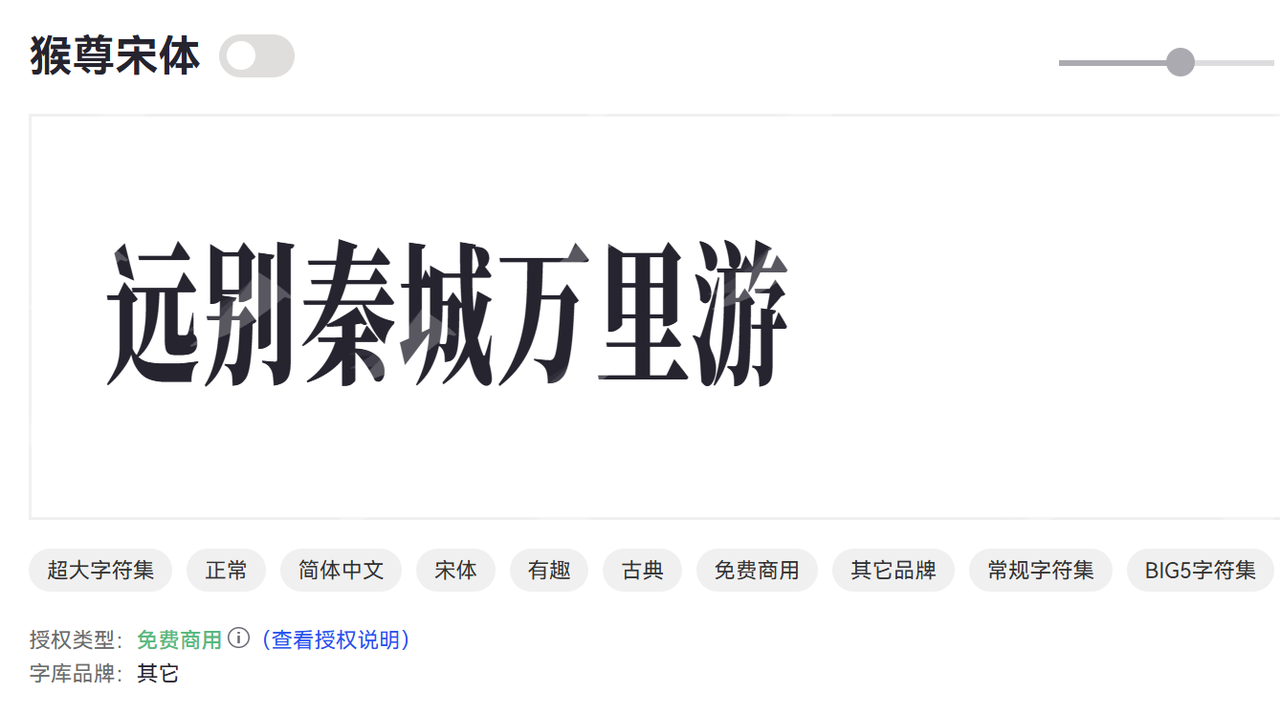
5、寒蝉活宋体
寒蝉活宋体是一款充满现代感的字体,具有动态的笔画表现。其流畅的线条使得文字在视觉上更加生动,适用于互联网文章、博客以及设计作品,能够吸引读者的注意。
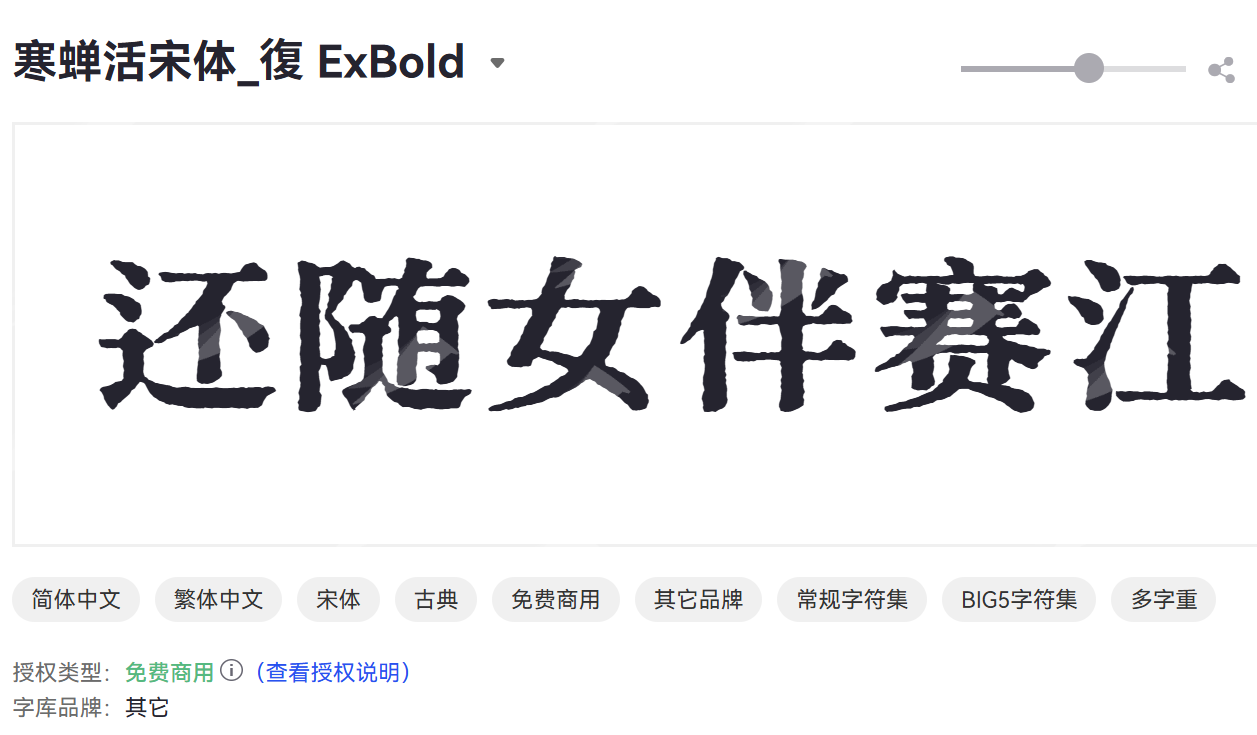
6、江城律动宋
江城律动宋是一款兼具古典与现代元素的宋体,字形稳重而灵动。该字体适用于各类正文字体,尤其是在书籍印刷和正式文件中使用,提升整体的文化氛围。
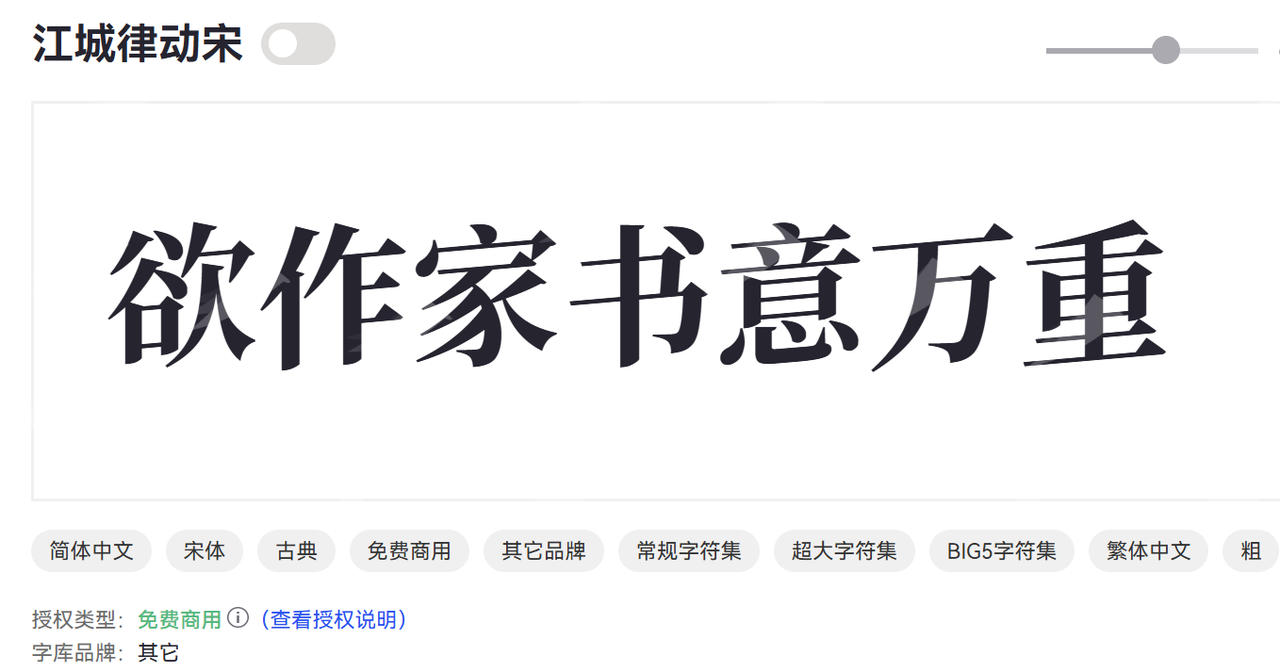
7、飞花宋体
飞花宋体是一款轻盈而富有艺术感的宋体字体,具有独特的设计风格。适合用于文艺类的设计项目、插画及装饰性文本,能够彰显出创意和美感。
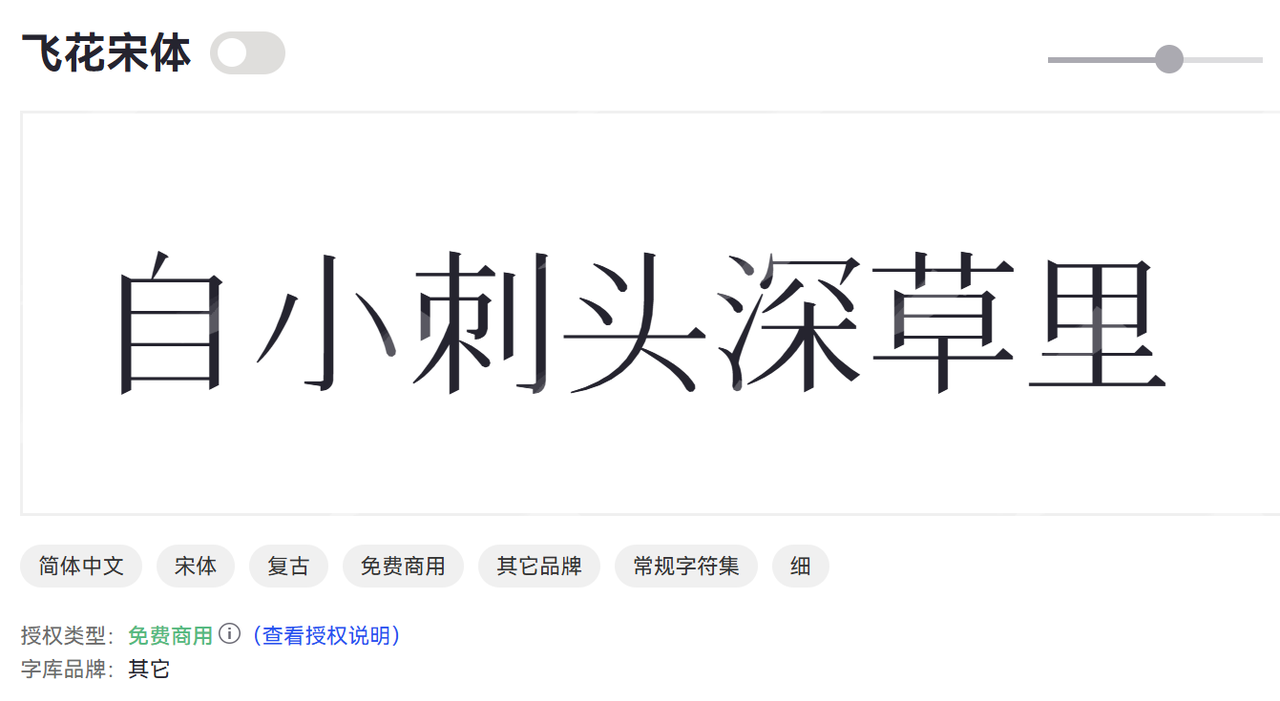
1、点字简宋
点字简宋是一款简洁明了的宋体字,强调实用性与可读性。适合用于各类普通文档和电子屏幕显示,能够保证信息的传达效率。
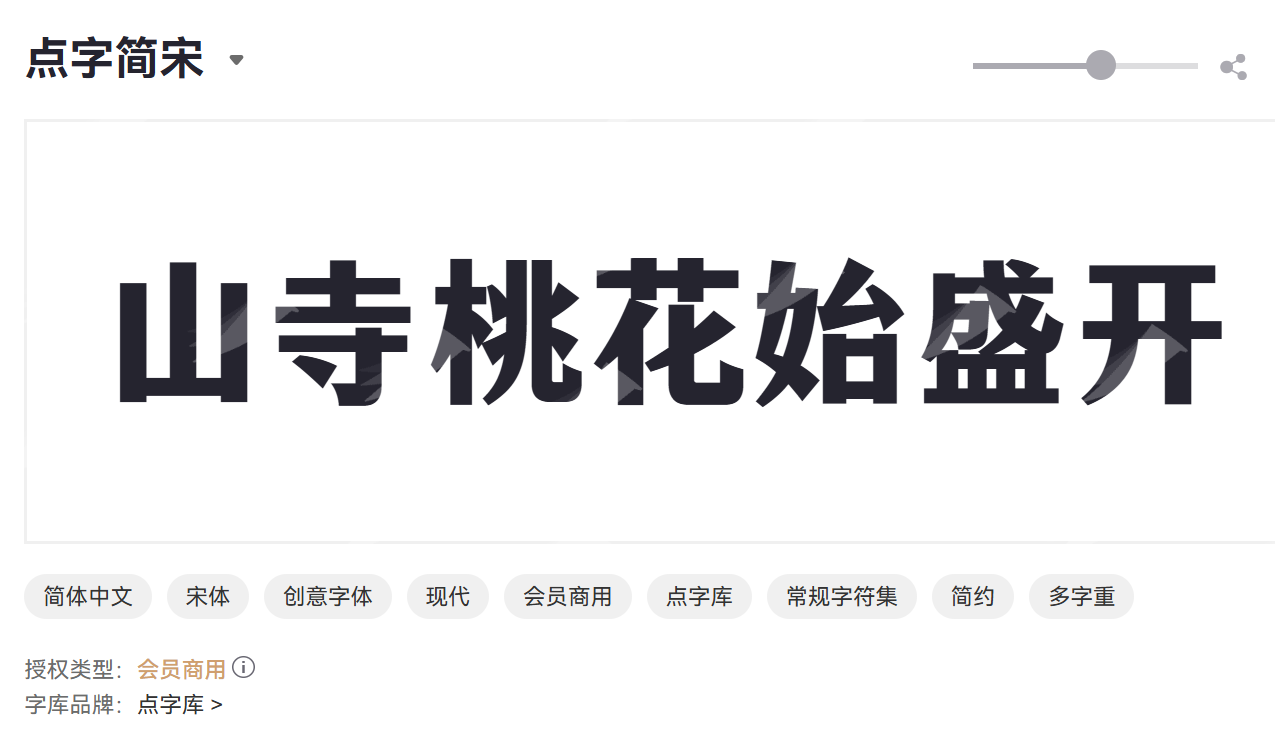
2、点字永胜粗宋
点字永胜粗宋是一款加粗的宋体字体,具有强烈的视觉冲击力。适用于标题和强调文本,在广告和海报设计中能有效吸引观众眼球,我比较喜欢在广告图片中使用点字永胜粗宋。
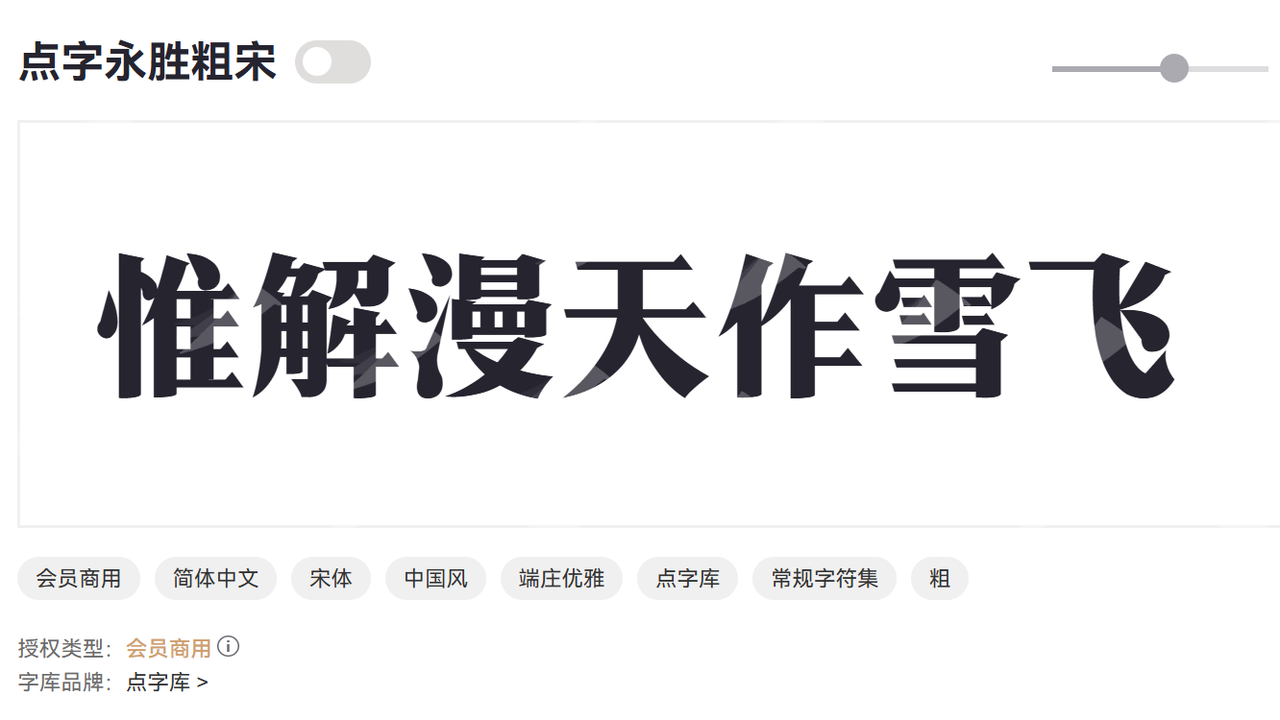
3、点字玄真宋
点字玄真宋是一款具有传统韵味的字体,字形优雅且大方。适合用于文化类书籍和高端品牌宣传,能够展现出深厚的文化底蕴,我发现很多的大品牌在做宣传海报时,会使用这款字体。
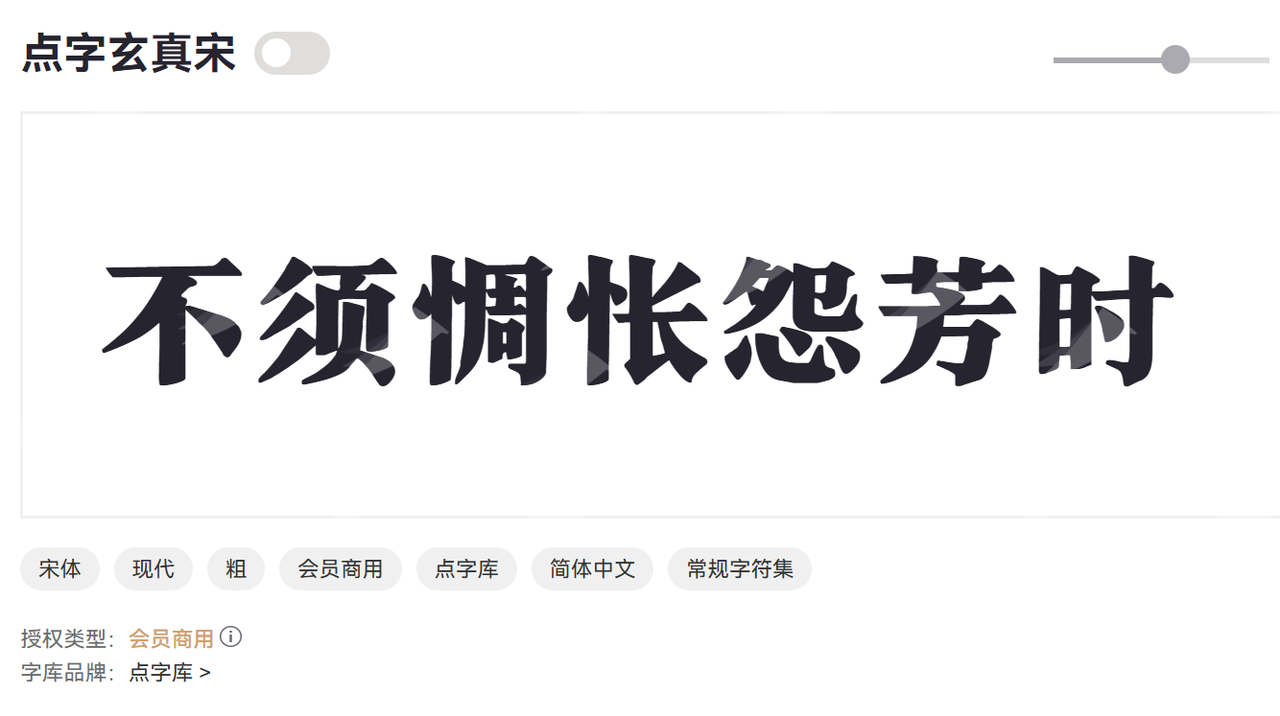
4、三极柔宋简体
三极柔宋简体是一款圆润柔和的宋体字体,字形流畅自然。适合年轻化的品牌设计和生活类内容,能够带来友好和亲和的视觉体验。
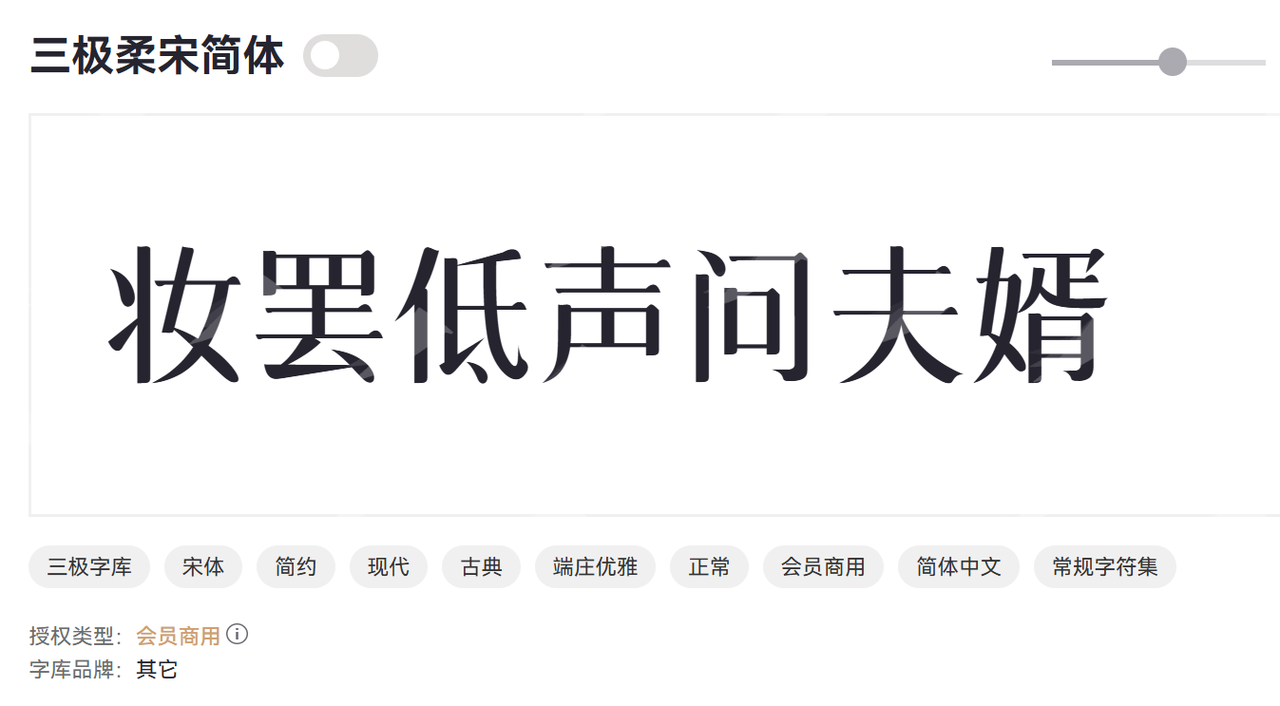
5、汉仪瑞虎宋
汉仪瑞虎宋以其独特的字形设计体现出力量与活力,适合用于品牌标识、广告宣传等领域,能够有效传达品牌的独特性和市场定位。
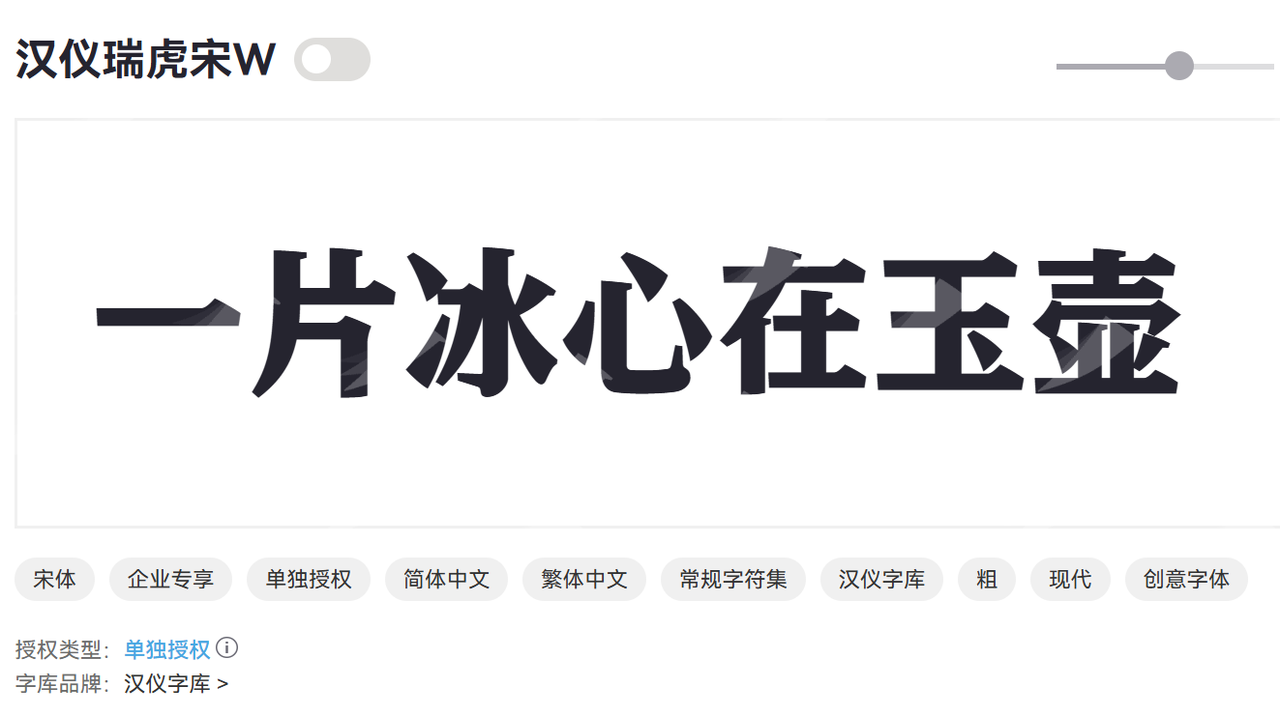
6、汉仪瑞云飞宋
汉仪瑞云飞宋是一款具有现代感的宋体,线条简洁流畅。适合用于科技类产品宣传及现代化的设计项目,能够体现出时尚与前卫。
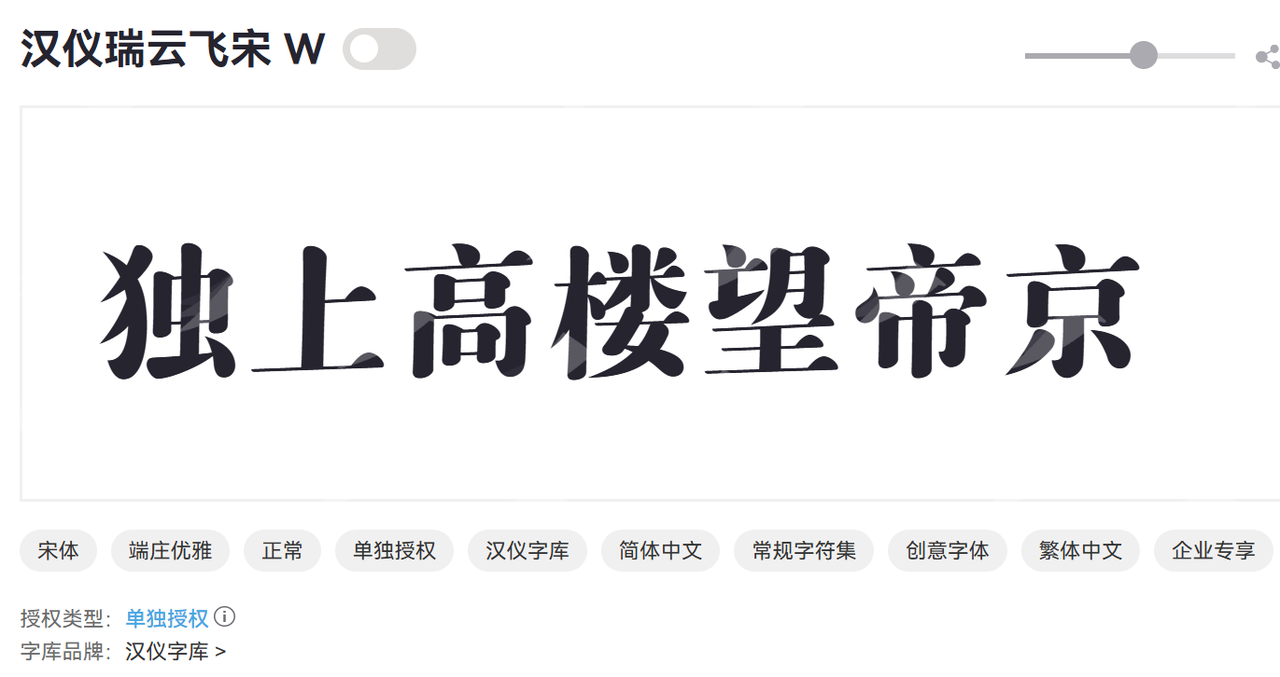
7、华康雅宋体
华康雅宋体是一款经典的宋体字体,设计上兼顾美观与可读性。适用于书籍、杂志及正式场合的文档,能够给人以稳重而专业的印象。